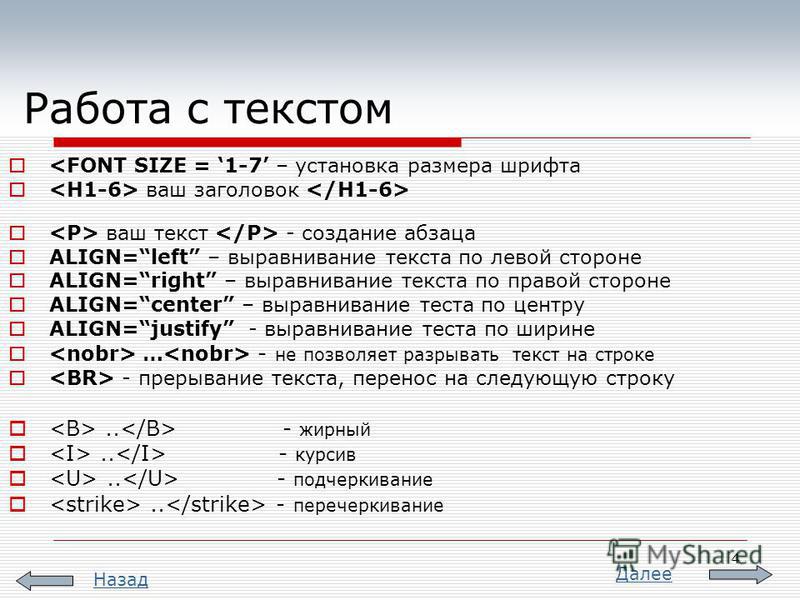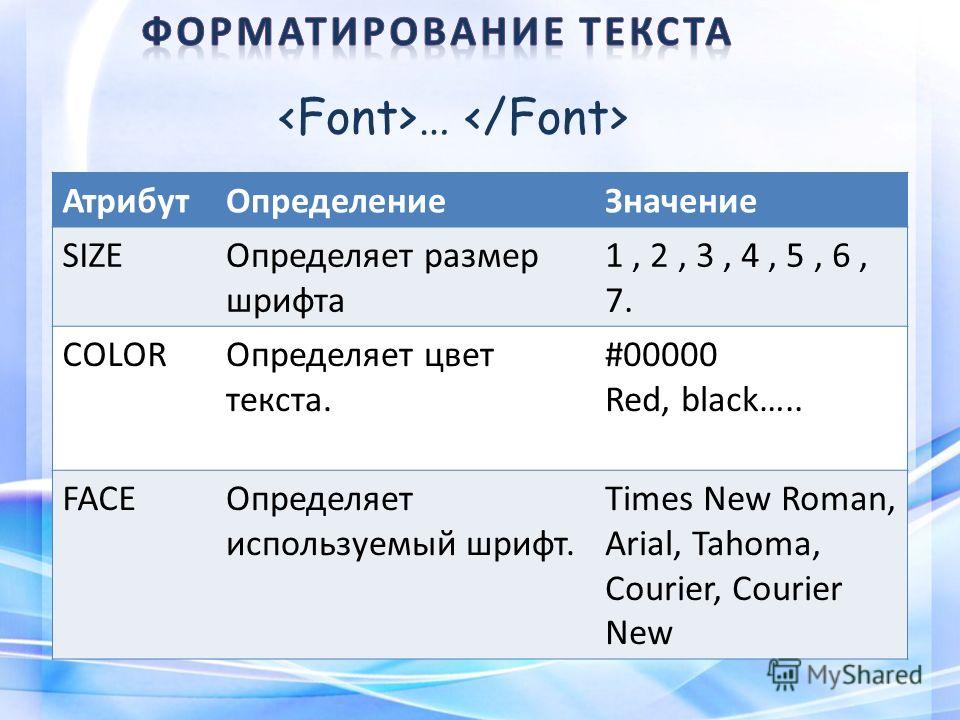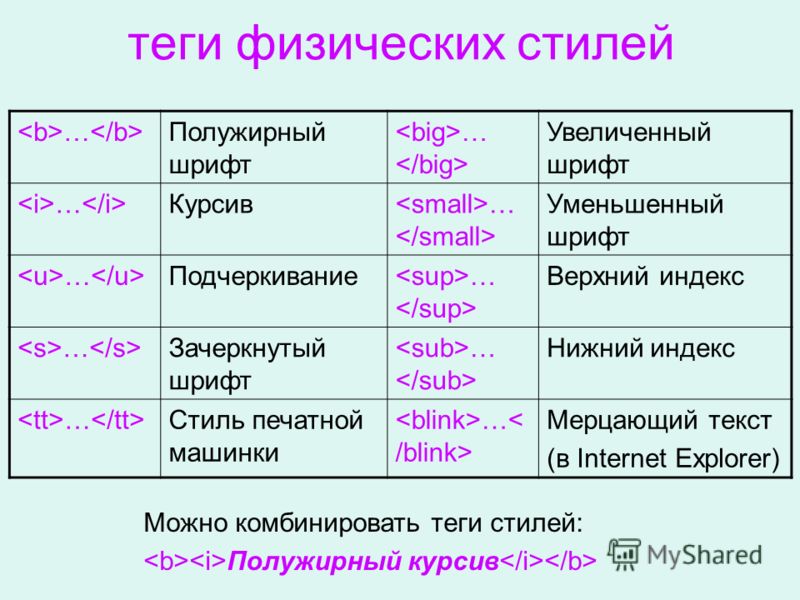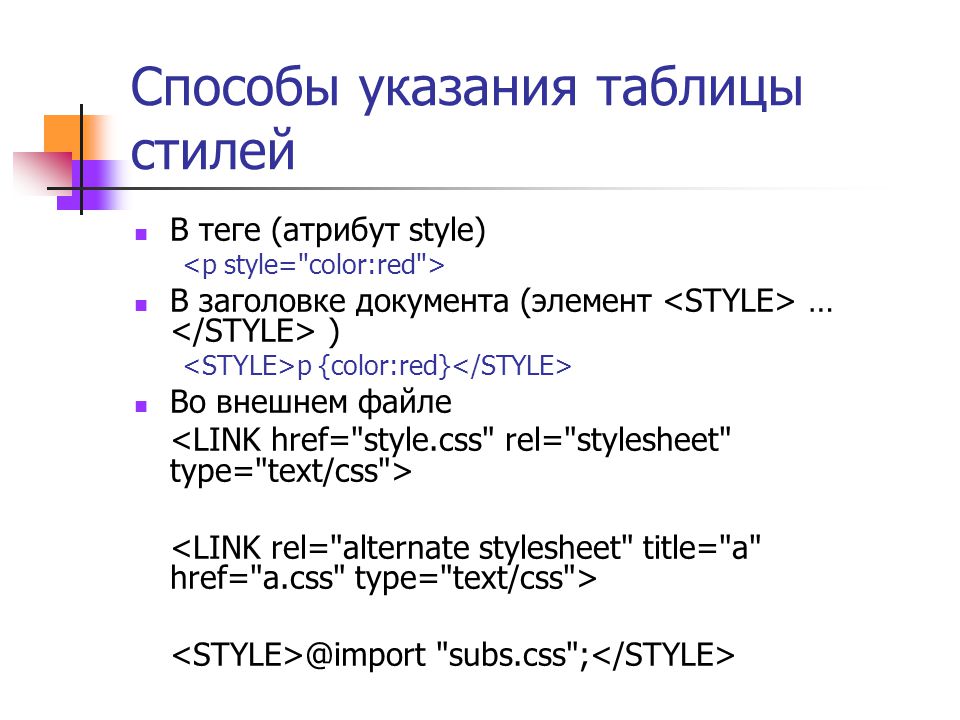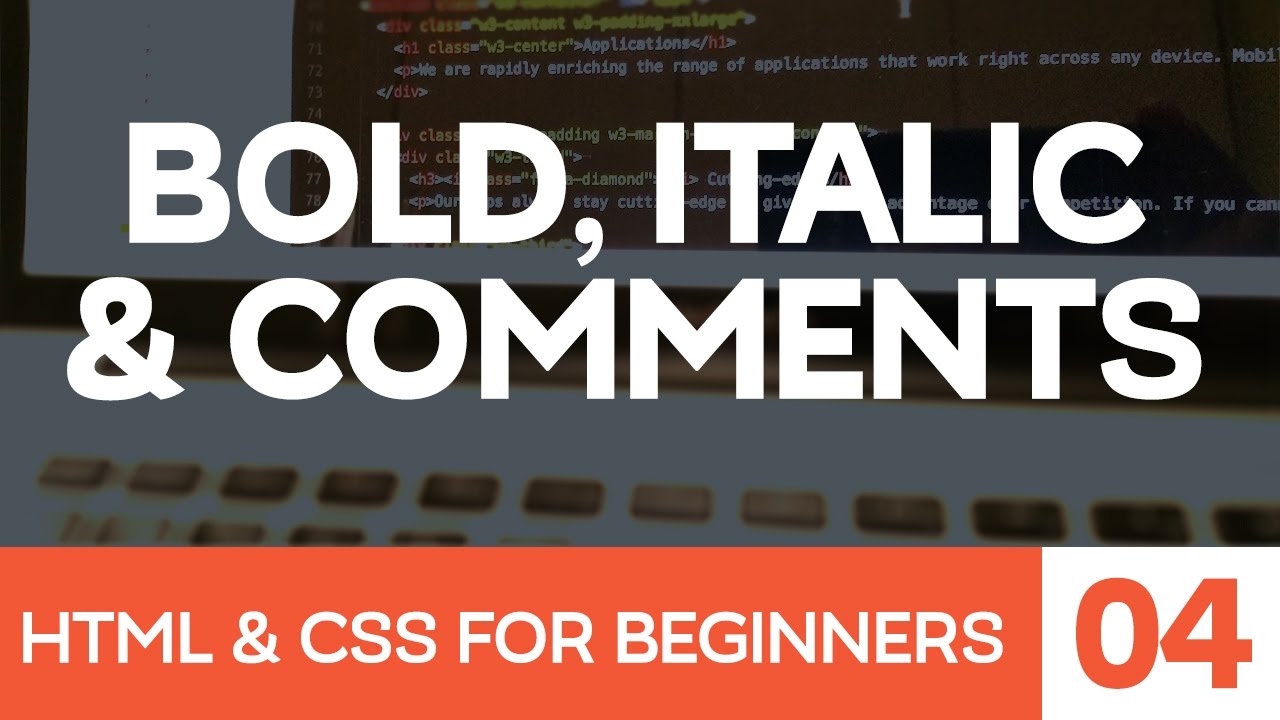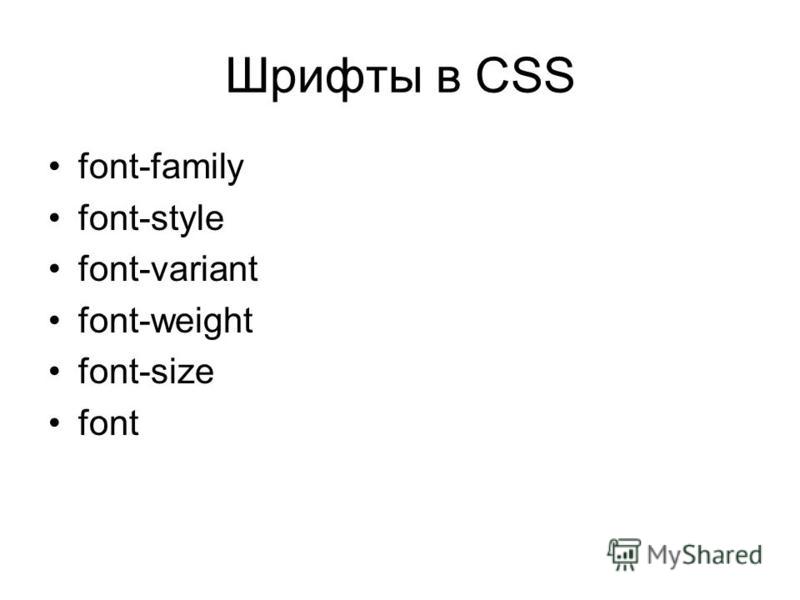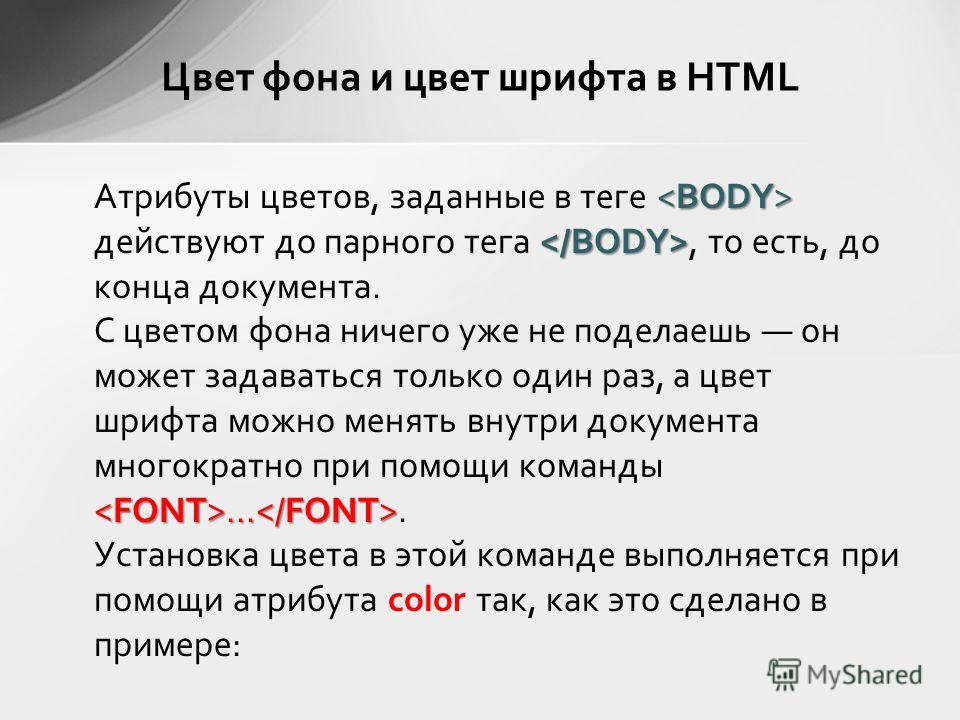
Html наклонный шрифт: Начертание | htmlbook.ru
Жирное начертание
Насыщенностью называют увеличение толщины линий шрифта и соответственно контраста. Обычно различают четыре вида насыщенности: светлое начертание, нормальное, полужирное и жирное. Однако с помощью HTML можно установить только нормальное и жирное начертание. Для установки текста жирного начертания применяется два тега: <b> и <strong>.
<strong>Сильное выделение текста</strong>Курсивное начертание
Курсивный шрифт представляет собой не просто наклон отдельных символов, для некоторых шрифтов это полная переделка под новый стиль, имитирующий рукописный. Курсив для текста определяют два тега: <i> и <em>.
<em>Выделение текста</em> Следует отметить, что теги <b> и <strong>, также как <i> и <em> хотя и похожи по своему действию, являются не совсем эквивалентными и заменяемыми.
В примере 7.5 показано использование тегов <em> и <strong> для оформления текстов.
Пример 7.5. Теги <em> и <strong>
</html>Результат данного примера показан на рис. 7.5.
Рис. 7.5. Жирное и курсивное начертание текста
Описание
Определяет начертание шрифта — обычное, курсивное или наклонное. Когда для текста установлено курсивное или наклонное начертание, браузер обращается к системе для поиска подходящего шрифта. Если заданный шрифт не найден, браузер использует специальный алгоритм для имитации нужного вида текста. Результат и качество при этом могут получиться неудовлетворительными, особенно при печати документа.
font-style: normal | italic | oblique | inherit
Значения
- normal
- Обычное начертание текста.
- italic
- Курсивное начертание.
- oblique
- Наклонное начертание. Курсив и наклонный шрифт при всей их похожести не одно и то же. Курсив это специальный шрифт имитирующий рукописный, наклонный же образуется путем наклона обычных знаков вправо.
- inherit
- Наследует значение родителя.
</html>Результат данного примера показан на рис. 1.
Рис. 1. Применение свойства font-style
Internet Explorer до версии 7.0 включительно не поддерживает значение inherit.
Браузеры текст со значением oblique всегда отображают как курсив (italic).
Наклон текста | WebReference
Наклон определяется сдвигом шрифта на определённый угол. Различают два типа наклона: просто наклонный шрифт (oblique) и курсив (italic). Курсивный шрифт представляет собой не просто наклон отдельных символов, для шрифтов с засечками это полная переделка под новый стиль, имитирующий рукописный. Следует отметить, что хотя браузеры и различают тип наклона italic и oblique, при этом они отображают текст как курсив.
Для создания курсивного текста применяются элементы <i> и <em>, а также стилевое свойство font-style. Следует отметить, что <i> и <em> несмотря на сходство результата в браузере, не совсем эквивалентны и заменяемые. Первый элемент <i> (сокращение от англ. слова italic — курсив) — является элементом для физической разметки и устанавливает курсивный текст, а <em> (сокращение от англ. emphasis — выделение, акцент) — элементом логической разметки и определяет важность помеченного текста. Такое разделение элементов на логическое и физическое форматирование изначально предназначалось чтобы сделать HTML универсальным, в том числе не зависящим от устройства вывода информации. Теоретически, если воспользоваться, например, речевым браузером, то текст, оформленный с помощью <i> и <em>, будет отмечен по-разному. Однако получилось так, что в популярных браузерах результат использования этих элементов равнозначен.
Чтобы различия были более заметны, добавим несколько классов с разным цветом текста (пример 1).
Так мы не только сделаем акцент на выбранном тексте, но и выделим его визуально.
Пример 1. Изменение цвета текста
Это полужирный шрифт.
Рис. 1.2. Примеры физического форматирования текста (браузером Netscape)
Тег
Тег отображает текст курсивом. Для большинства случаев вместо этого тега рекомендуется использовать теги , , или , поскольку последние лучше отражают назначение выделяемого текста. Например:
Выделение курсивом
Тег
Тег отображает текст моноширинным шрифтом. Для
большинства случаев вместо этого тега лучше использовать теги , или . Пример: